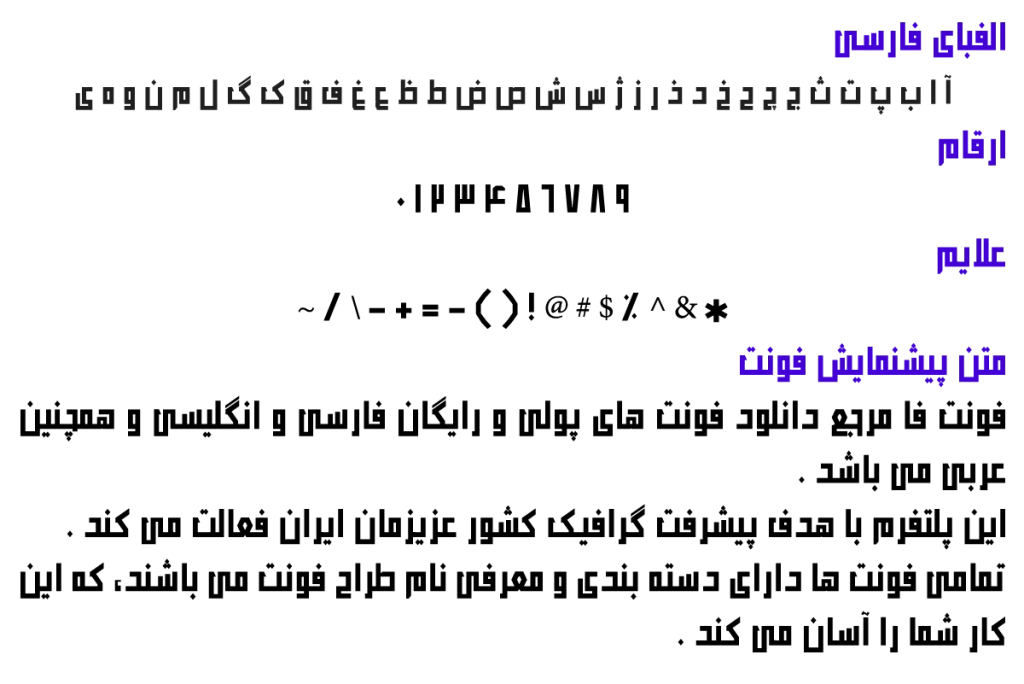
فونت فارسی نرمال – Mj Normal
مجموعه فونت: فونت سری Mj
طراح فونت: مجتبی کیا نوع فونت: فونت هندسی
پیشنمایش فونت نرمال
توضیحات و معرفی فونت نرمال
فونت فارسی نرمال ( Mj Normal ) از مجموعه فونت های سری Mj می باشد، و نیز نوع فونت هندسی و اسلیمی می باشد.
فونت خوشگل مربوط توسط مجتبی کیا در سال 1390 طراحی و ساخته شده است.
و نیز فونت Mj Normal در یک وزن پر رنگ است.
در تصویر زیر می توانید شعر زیبای «وطنم» را که با این قلم نوشته شده، تماشا کنید.